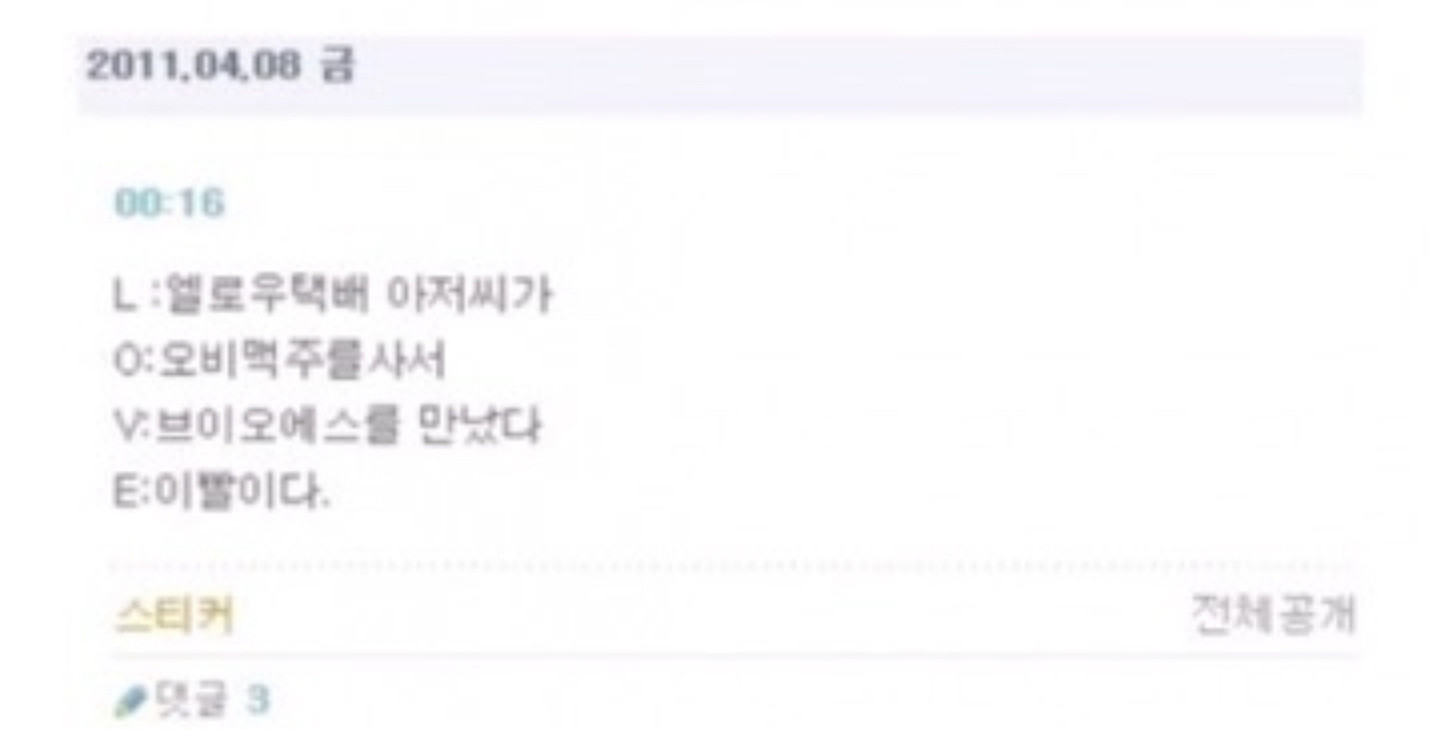
싸이월드 기본 폰트인데 도대체 뭐죠? 눈누에 있는 레트로 글꼴.. 둥근모꼴 이런거 다해봤는데 아니에요 ㅜㅜ 제발 싸이월드 기본 폰트 다운받는법 아시는분..
굴림
윈도우 기본내장폰트입니다. 웹상에서 11pt 이하로 쓰면 저렇게 나옵니다
돋움
굴림 아니고 돋움입니다. 윈도우 기본 한글 폰트 중 하나이고 9pt 크기입니다.